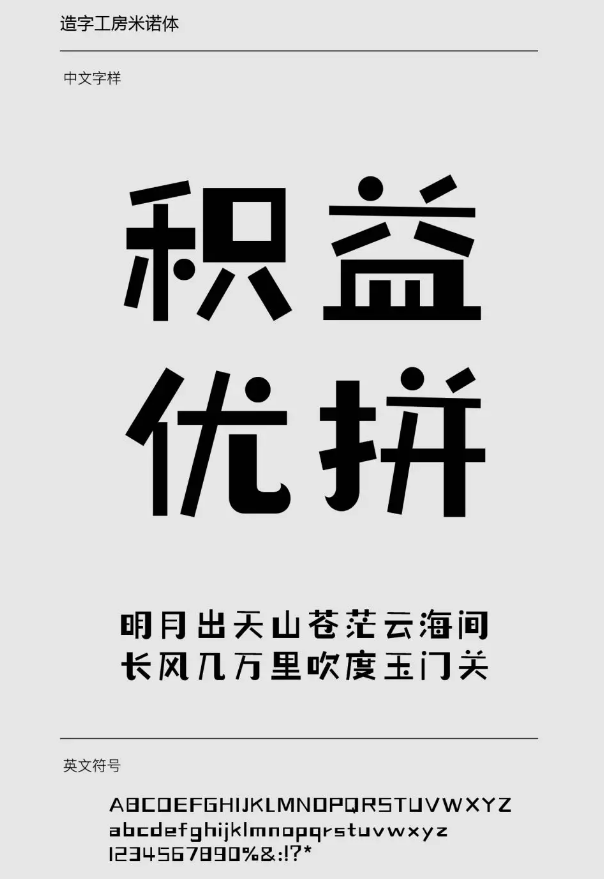
造字工房米諾體字體中宮寬闊、字面飽滿,筆畫粗細(xì)穿插有序,點(diǎn)畫巧用圓點(diǎn)使得此套字體寬博又不失靈動(dòng),神形兼?zhèn)?,風(fēng)格隨性自然,活潑俏皮。此款字體適用于兒童讀物、報(bào)刊雜志標(biāo)題、廣告設(shè)計(jì)等視覺環(huán)境,有著極強(qiáng)的應(yīng)用空間。歡迎喜歡造字工房米諾體的朋友前來下載使用。